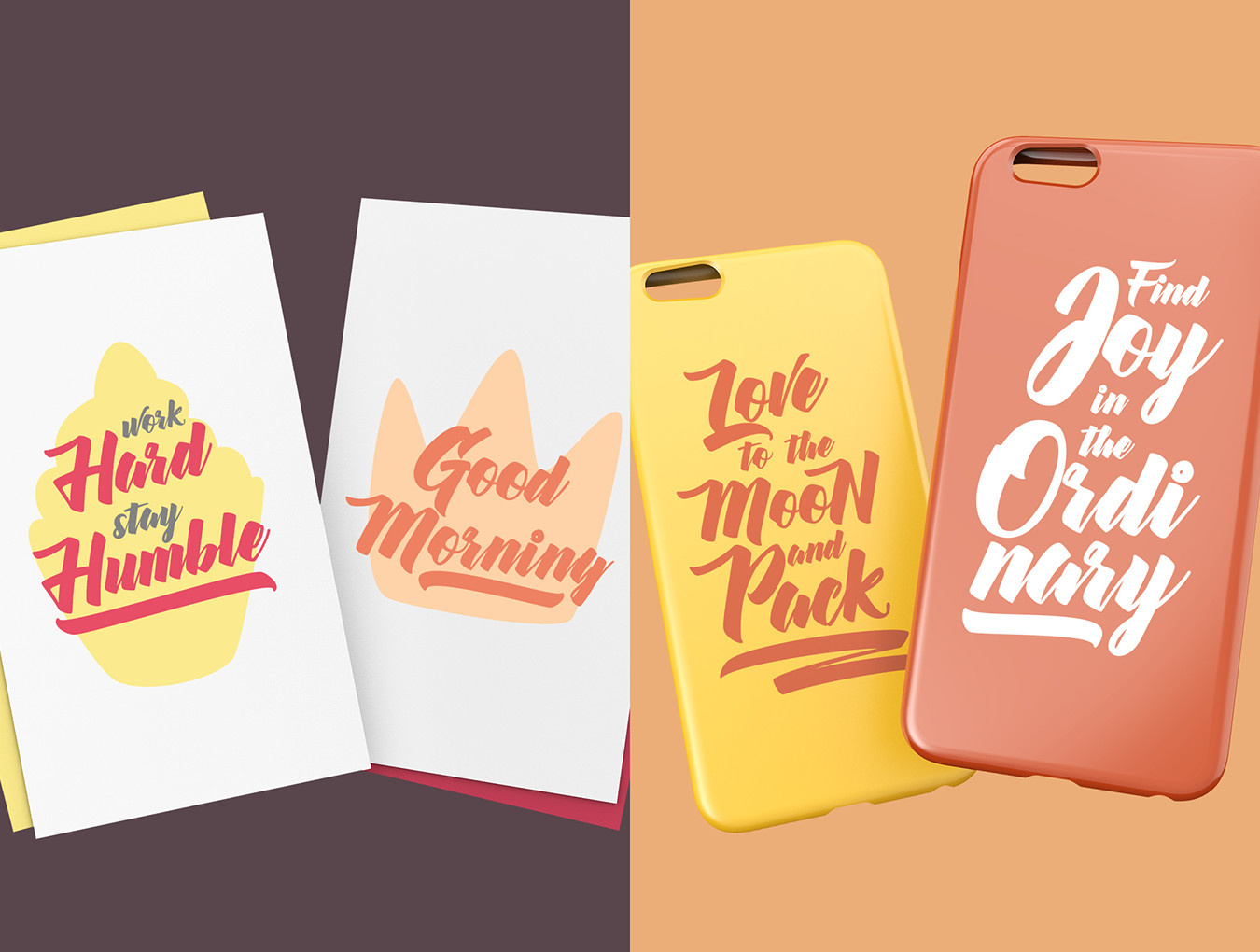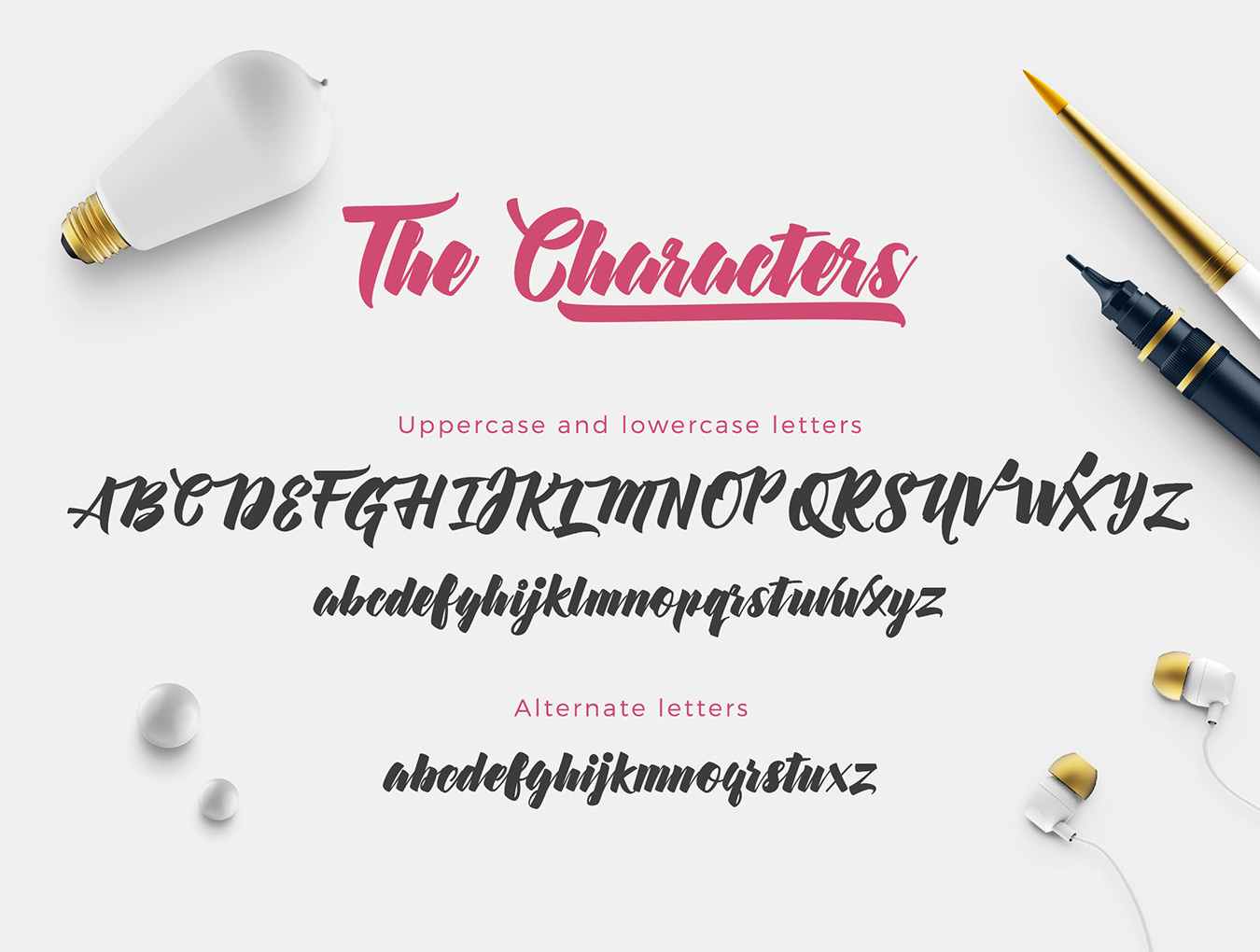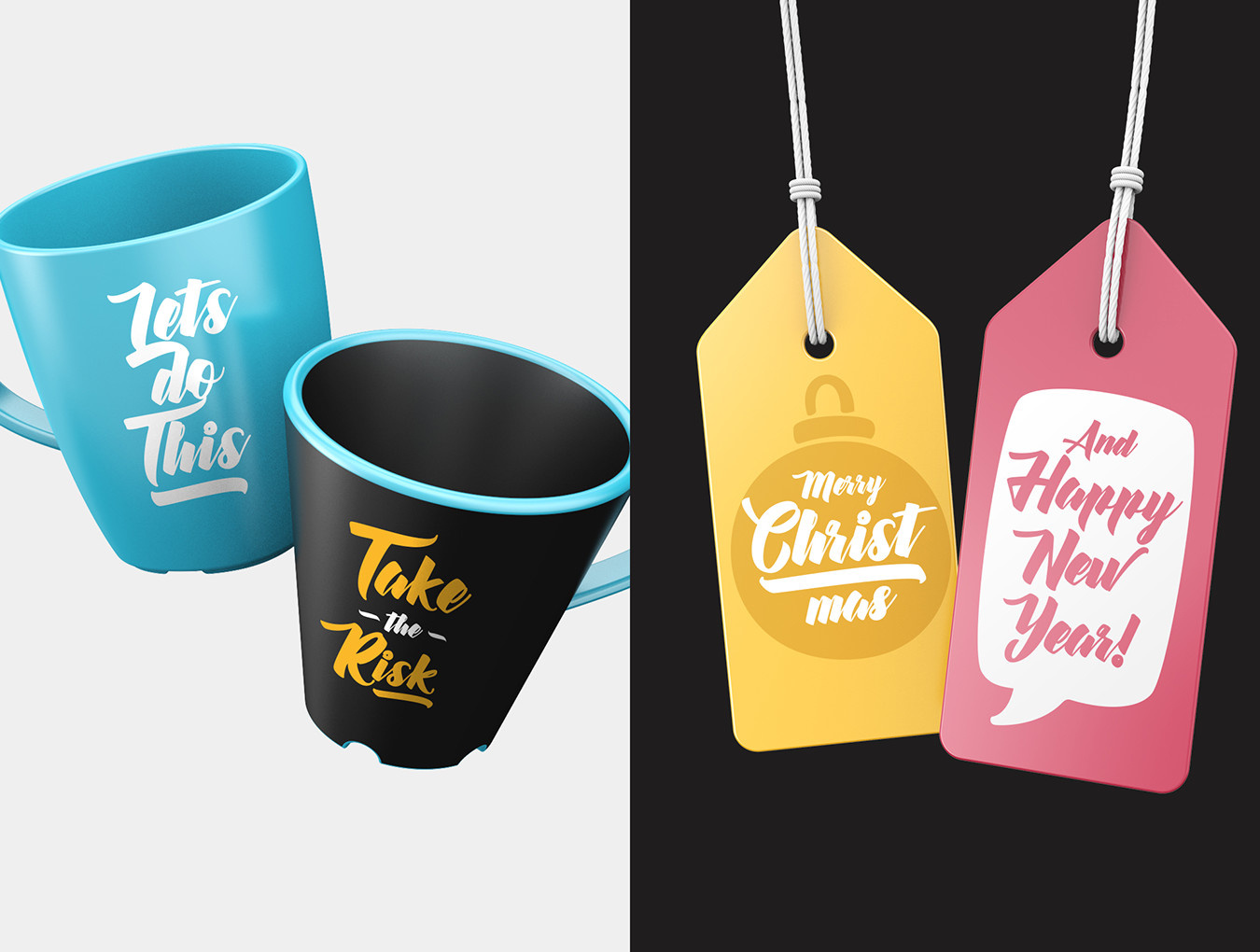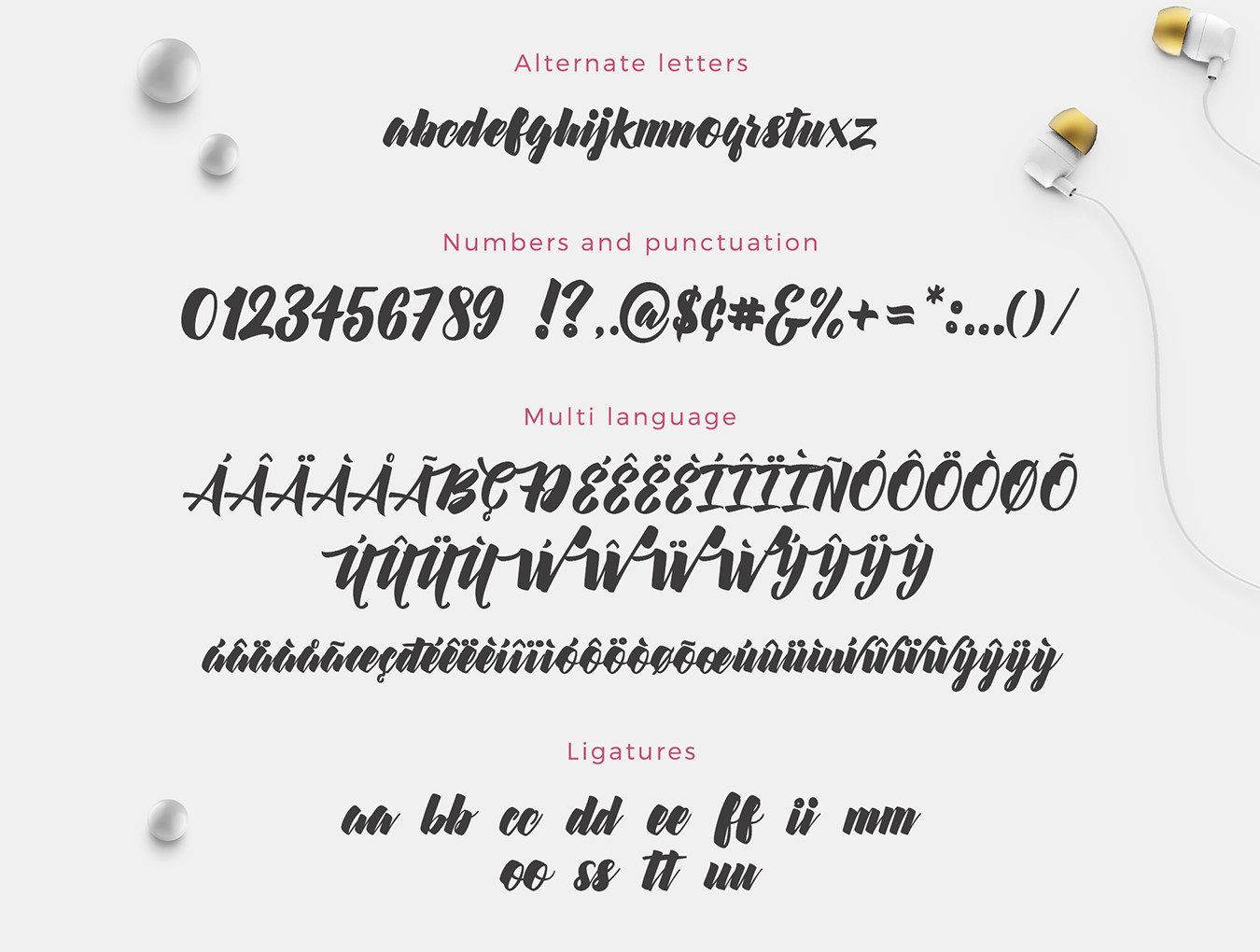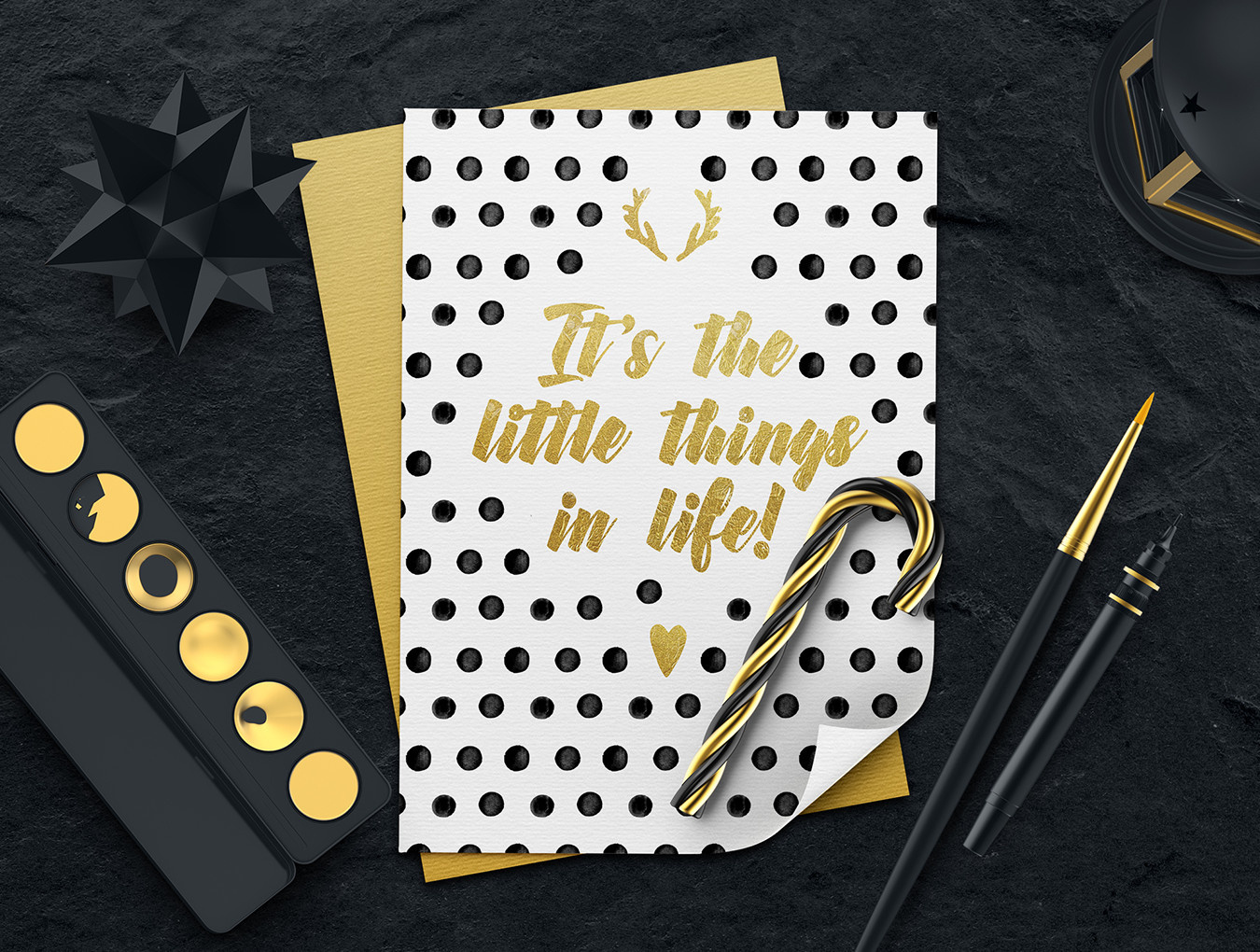
完美的脚本刷字体 - 只为你!,日内瓦脚本字体
Perfect script brush font - just for you!, Geneva Script Font
日内瓦是一种手绘字体,具有独特而优雅的笔刷风格,非常适合信笺,服装设计,标题,标识,海报,卡片等。对于拥有opentype软件的人来说:可以通过打开'Stylistic Alternates来访问替代品'和'Ligatures'按钮在Photoshop的Character面板中,或通过任何带有字形面板的软件,例如Adobe Illustrator,Photoshop,Inkscape。 对于那些喜欢的人,我已经包含了一组相应的TTF文件。